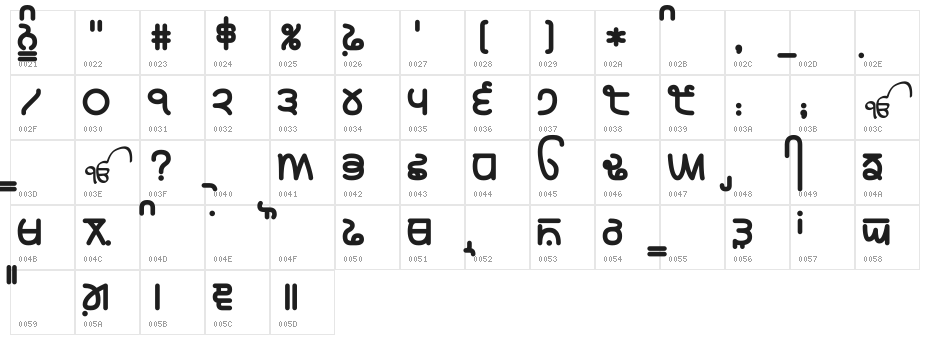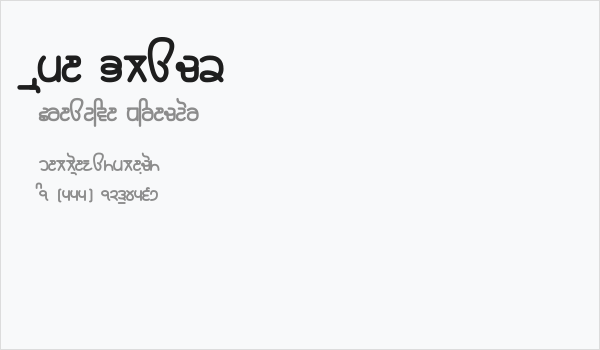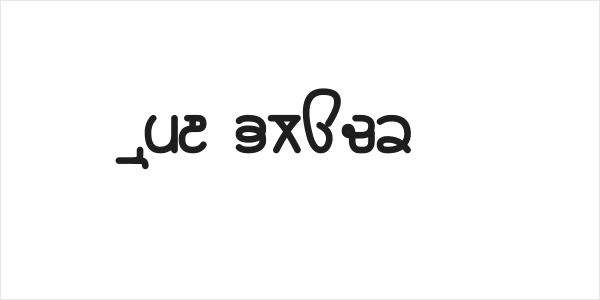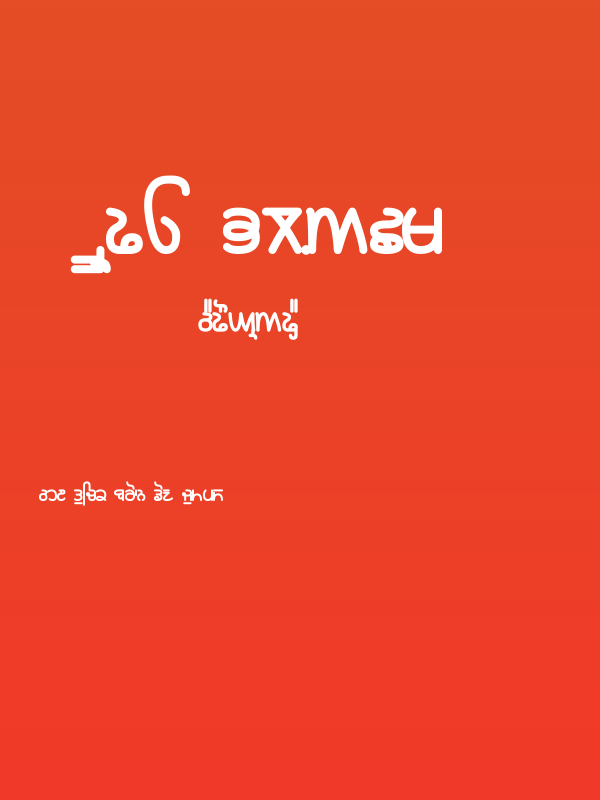
Rupe Black Font
| 整体风格 | Modern, Decorative |
| 使用场景 | Logos, Headlines, Artistic projects |
| 推荐项目 | This font is perfect for use in creative design projects such as album covers, posters, digital art, and branding for modern and innovative companies. |